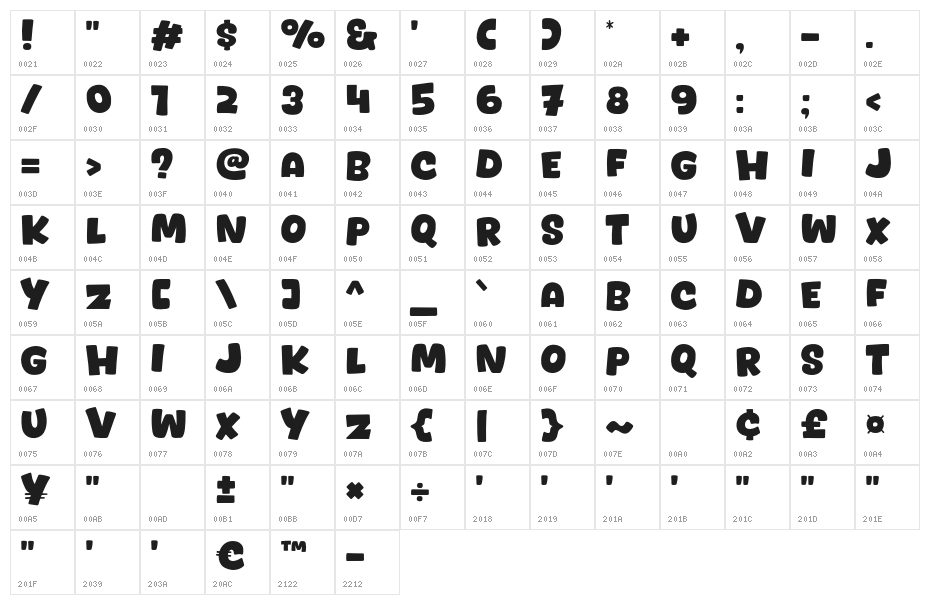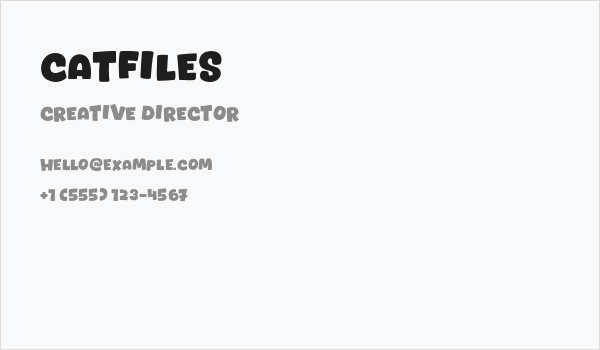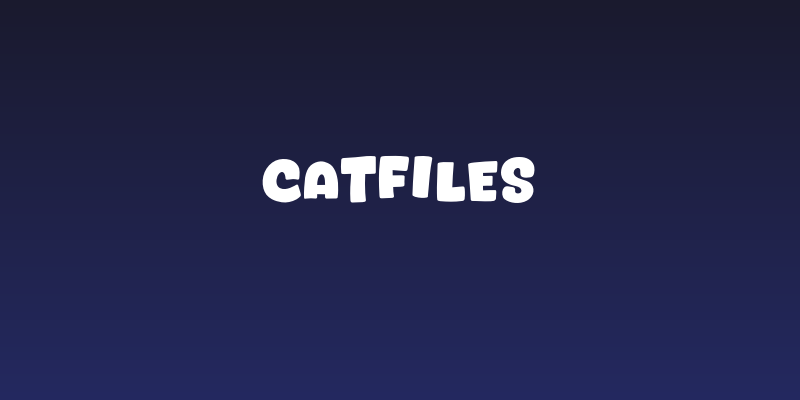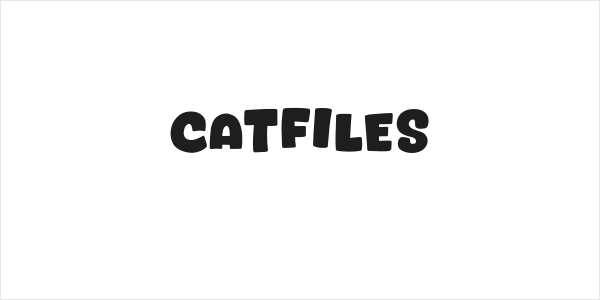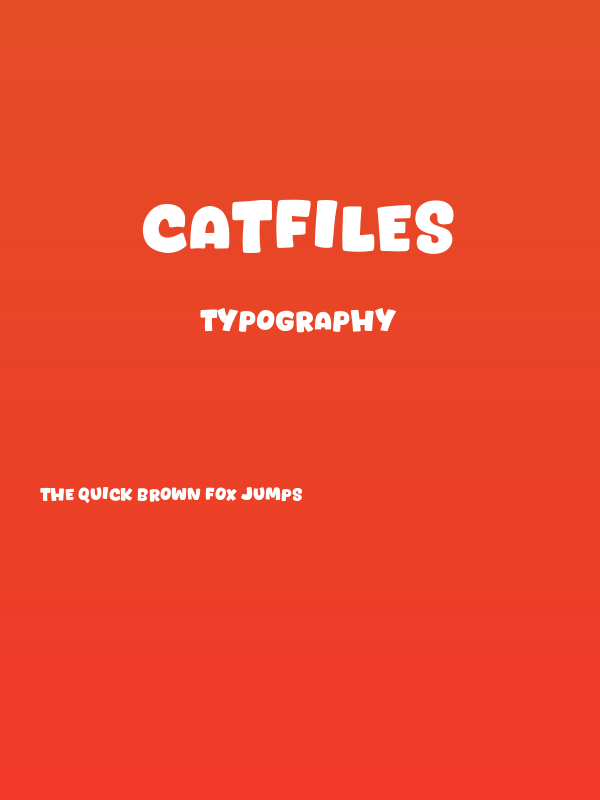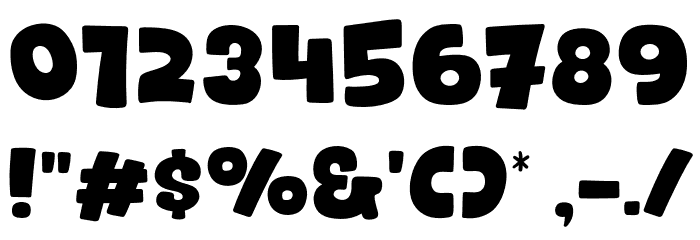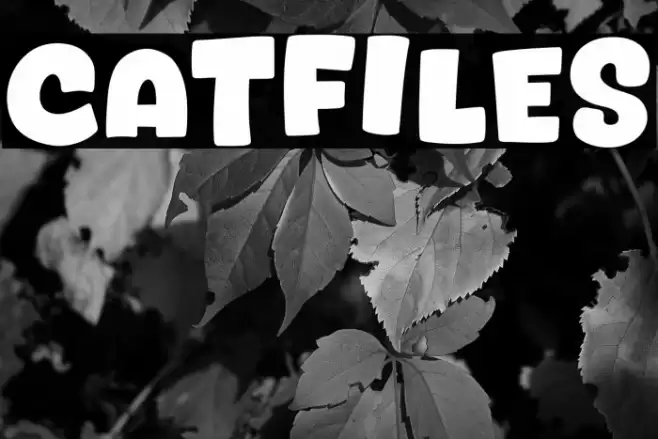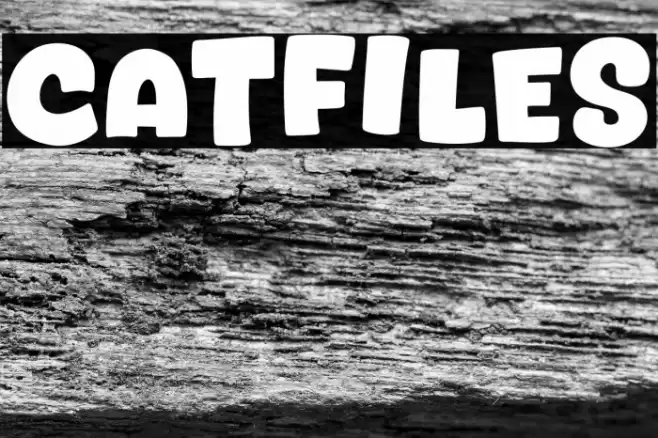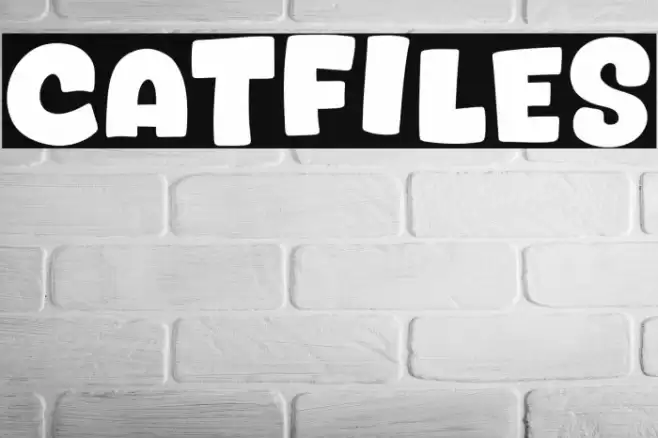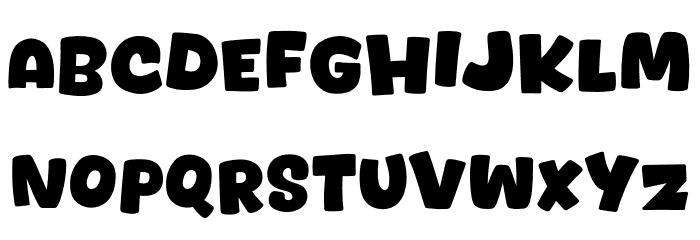
Catfiles Font
| Estilo general | Playful |
| Proyectos propuestos | Ideal for children's books, playful branding, party invitations, and cartoon graphics. |